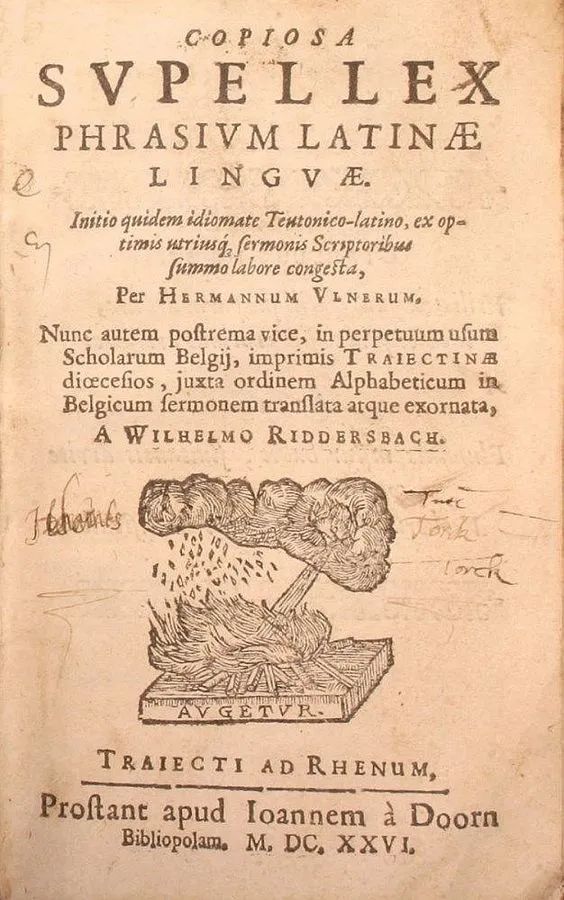
版式设计中文字的设计技巧分享
继版式三部曲之构图篇结束之后,时隔几个月终于迎来了这个系列的第二篇内容,就是“文字篇”。对上一篇内容还有印象的同学,应该记得我在结尾处预留的一个预告,当时我说的编排细节就是“文字”,为什么是文字呢?因为我们在排版时除了处理图片之外,剩下的就是要编排文字。今天的这篇文章也将围绕着“文字”展开,相信大家看完后会对“文字”有一个全新的了解,也将明白文字对于版面的意义是巨大的,处理好它,基本上你的版面也就编排的差不多了。好了,下面我们开始今天的内容吧。
首先来看几张不同类型的海报,第一张文字占比较高,第二张图片占比较高,第三张文字与图片占比是五五开。
然而不管是属于哪种类型的,它们的核心目的都是在传达信息。因为对于一张海报来说,我们不光会看还会去阅读它们。
平面设计就是通过文字来“说话”的。
而在广告设计中,图片的占比会非常高,因为广告多以图片为主,通过图片我们能大致的猜测出设计师想要表达的东西是什么。
总结一下:广告设计多以图片为主,意在通过图片传达概念;而平面设计则多以文字或图片为主,意在通过文字传达信息。
那么作为信息传达的载体,字体就显得格外重要了。下面我会从字体的分类、字体的搭配、字体的气质与设置细节着手,慢慢带领大家去认识字体,首先我们来看看字体的分类都有哪些。
其中书法体又细分为:楷书、行书、草书与隶书等。
在列举的这些字体中,最常用就是:黑体、宋体和圆体,而在书法体中,最常用的是楷书与行书。为什么说这些字体常用呢?因为在许多优秀的设计作品中,这些字体的出现概率都非常高,尤其是黑体与宋体。
其中最常用的就是:衬线体与无衬线体。理由与中文一样,它们也是使用率很高的字体,其次还有一个原因就是在以中文为主的设计中,它们与中文字体搭配起来比较契合。
拿黑体来说,与之搭配的英文字体就是无衬线体,因为它们的笔画特征相似度很高。
宋体搭配的就是衬线体,因为宋体的笔画特征是有粗细变化且有装饰线,而英文的衬线体也刚好有与之相似的地方。
而圆体则是搭配拥有相似特征的无衬线体。
因为常用的书法体通常使用毛笔书写,所以在笔画特征上没有与之相匹配的英文字体,大多数时候我们会选择用衬线体来搭配,具体原因我会在后面的字体气质环节为大家讲解。
虽然也有别的搭配方式存在,但我给大家提供的这些都是最常用和最安全的。说完字体搭配问题后,下面我们来看看这些字体,所包含的气质又有哪些。
首先是黑体,它具有科技感与现代感,这是由它简洁干练的笔画特征决定的。
其次黑体也能表现出运动与时尚的感觉,因为运动与时尚本就是偏现代的词汇。
接着是宋体,它具有文化与历史的气质,这个比较好理解。
而除了能表现出历史与文化感之外,宋体还能表现出清新与雅致的感觉,这是由宋体的笔画特征决定的,横细竖粗且末端带有装饰,与优雅精致的感觉十分契合。
圆体的特点也是非常明显的,在看到它时脑海中的第一印象就是可爱与卡通。
除了刻板印象外,圆体那种圆滚滚的笔画给我们的感觉还有安全和易亲近,所以圆体也能用来表现儿童与温暖感觉的题材。
一说到书法体,能直接联想到的关键词就是传统与历史,因为书法的演变就是我们汉字发展的轨迹。然后我们回过头来讲一下,为什么书法体可以和西文中的衬线体搭配。
原因就在于衬线体也具备书法体的某些气质,比如传统、文化、历史等。与书法体在早期的东方一样,衬线体在早期的西方也是主要的字体之一。
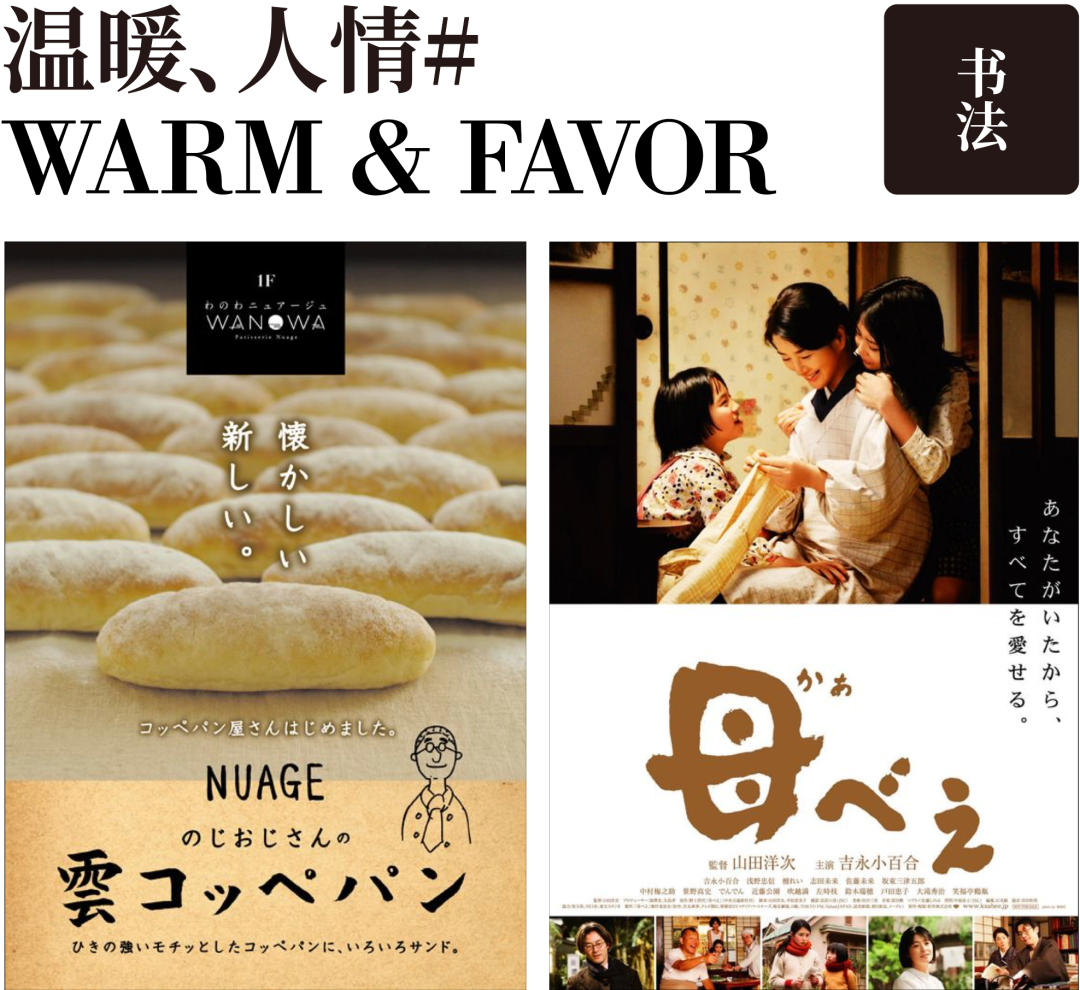
温暖、人情味儿,说到书法体可能很难联想到这两个词,但是书法体确实具备这种气质。跟黑体这种棱角分明的字体相比,书法体是手写出来的,它的笔画特征给我们的感觉就是有“温度”的。
在字符面板中,除了选择字体与改变字号以外,这两个区域相信大家用的还是比较多的,它们分别是:行距设置与字距设置。
拿行距来说,在使用时有几个比较常用的设置方法,比如用当前文字的字号乘以1.2、1.732或是2。不过,通过这个方法所算出来的数值只是一个参考,也就是说你可以在这个基础上做些调整。
比如:在计算出的数值的基础上进行递增或是递减,这时你要做的就是用眼睛去观察,觉得大了就减少一些,觉得小了就增大一些。
其中,用字号乘以1.2适用于标题。
比如上方那个标题的字号是40pt,那么行距的数值就是用40乘以1.2等于48。下方这个是在此基础上做的一个调整,稍微增大了一些行距。
字号乘以1.2适用于标题,而用字号乘以1.732或2则更适用于小字号的文字,比如内文。
上方是用字号乘以1.732的例子,字号是9pt,用它乘以1.732得出来的数值是15.588,四舍五入取个整数得到的行距就是16,下方这个是用字号乘以2得到的效果。
大多数情况下我建议大家用字号乘以1.732的行距,大小比较适中。
跟行距不同的是,基本上来说字距是无需调整的。当然还是那句话,要靠自己的眼睛来衡量,如果你觉得字与字之间离的很近的话,那么可以增大一些字距,反之,则可以减小一些。
其次就是,当你遇到一些偏轻松慢节奏的设计,比如典雅清新类的文学小说时,就可以适当的增加一些字距来营造这个感觉。
比如这两张海报,左边的是经典的居中结构,右边的是包围结构,构图都是可以的没有任何问题,但为什么看起来还是怪怪的呢?因为文字组没有刻画好。
为了让大家能更深刻地体会到文字组对于版面的意义,修改了这两张海报,其中构图不变只改文字组。
这个修改前后的对比还是非常直观的,可见文字组对版面的影响有多大。如果说构图是版面的骨架的话,那么文字组就是版面的五官,骨架再好五官不行结果也是可想而之的。
文字组分为:左对齐、居中对齐、顶对齐以及两端对齐。
其中与左对齐与顶对齐对应的有:右对齐与底对齐。
给大家找了一些各种对齐方式的案例。这是左对齐的形式。
这是右对齐的形式,与左对齐相比右对齐属于不常用的对齐方式,主要是出于易读性的考虑,但并不是说不能用。
这是居中对齐的形式,最经典的对齐方式之一。
这是顶对齐的形式,是文字竖排时最常用的对齐方式。
这是底对齐的形式,跟顶对齐相比也是属于不常用的对齐方式。
最后是两端对齐的形式,横排与竖排都可以使用这种对齐方式。
如果作品看得足够多,应该见过这种形式的组合,它同时包含了多种不同对齐方式,我们称其为“对齐组合”。
比如我们可以借鉴结构,以这个文字组为例,它的结构是这样的:两端对齐、中间的文字字号大,上下的文字字号小,按照这个套路我们来试着做一个组合。
在编排前,我们先阅读一下文案,通过文字可以得知,这是一个与篮球明星有关的内容,气质上来说会偏现代一些。
所以字体可以选择一款黑体,英文部分则搭配一款无衬线体。
根据之前总结到的这些特征,下面就可以开始编排文字了。
按照那个组合的套路,我们先将两端对齐中较大字号的文字给编排出来,而标题信息无疑是非常适合用来放大的。
接着再将上方和下方的小字号文字给编排出来。
其中要注意的就是这段文字的行距,我参考了logo的高度来进行设置。而整个组合中,字距是基本没有进行调整的。
值得一提的是,在两端对齐的文字组中,这种小大小的形式非常好用。因为它的节奏变化丰富,所以大家在做两端对齐的文字组时不妨试试。
这就是借鉴结构的效果了,精髓在于要多去分析别人的形式与套路,并从中获取做组合的灵感。除了能借鉴结构之外,我们还可以借鉴标题字数+结构,是什么意思呢?
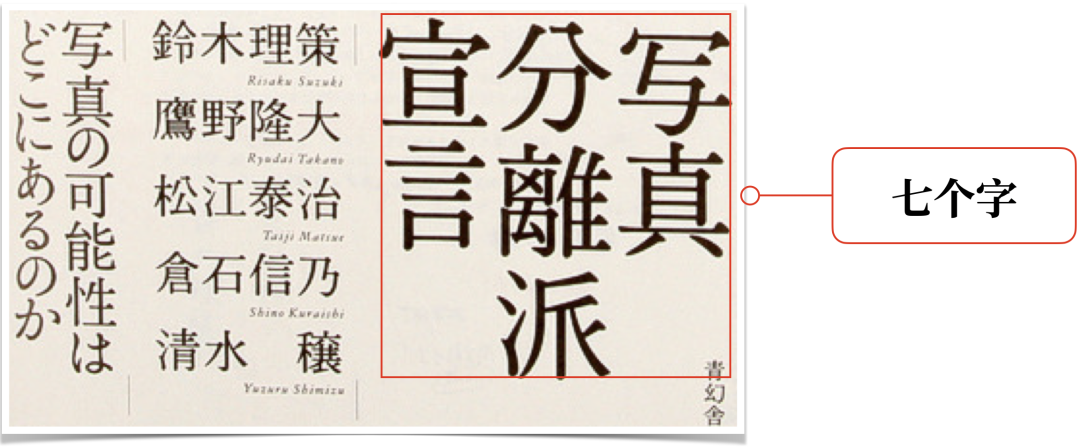
以这个组合为例,它的标题有7个字,整个组合是由顶对齐与两端对齐构成的一个对齐组合。
它的组合结构为小中大,按照这些特点我们来尝试借鉴。
这是要用到的文案信息,通过阅读文案可以得知,这是一个关于炸鸡套餐的内容。
通过去看kfc的各种物料,发现运用黑体的场景还是比较多的。
所以,在字体搭配上选择用黑体与无衬线体。
根据之前总结到的这些特征,下面就可以开始编排文字了。
按照小中大的特点,依次将信息给编排出来。
完成后可以在组与组之间,添加一根小线段用于连接,以起到过度的作用,如果大家现在回过头去看原图的话,也能发现这一特征。
其中,标题的行距就是用标题的字号乘以1.2算出来的。
字距我也做了调整,因为默认0的字距看上去有些拥挤。
可以看出跟原图相比,在不破坏组合结构的情况下,针对文字信息的编排是做了些调整的,比如:原稿最左侧是两行顶对齐的小文字,在借鉴时将它换成了logo,因为我们是要借鉴它的结构,而不是为了跟原稿做的一模一样,具体还是要根据我们的内容来合理编排。
首先我们来看这张图,一个标准的两端对齐、组合结构与之前那个是一样的,中间的字号大,上下的字号小。
除去这些外还有一个小特征就是,在大字号中间还有一层小字号的文字。
接着我们再来看这张图,它的特点就是图片叠压在了文字的上方。至于它的结构我们可以不用考虑,因为结构已经找好借鉴了。
这是要用到的文案与图片。通过文字可以得知,这是一个关于介绍昆虫的图书,且配有一张插图。这个插图的风格是手绘形的,偏写实一些没有那么的卡通。
结合这些特点我选择的字体搭配方式是,宋体配衬线体。
因为字体搭配这部分我又借鉴了一些相关风格的书,发现它们的字体搭配方式用宋体比较多。
分析完文案找到字体搭配方式后,在结合之前总结的一些组合特征,我们就可以开始编排了。
先将中间比较大的那层文字给编排出来,然后在它中间处置入一个小字号的文字。
中间层编排完成后再来编排上下层的文字,字号不用太大,整体注意好两端对齐。
调整字距的地方有两处,首先是标题,调整的原因在于默认值我觉得有些小了,其次是标题中间的那行文字,调整它的原因在于不想字号放太大。
因为是两端对齐的结构,不调整字距的话。标题中间那行文字只能通过放大字号来达到目,然而这个效果并不是我想要的。
综合考虑,选择了这个,最后,把图片置入进去叠压在文字的上方。
图叠压在文字上有一个无法避免的问题就是,被压住的文字会出现无法识别的情况,英文还好但是中文却不行,因为在这个组合中,中文是用来阅读的文字,英文仅充当装饰用。
既然中文是重要的信息,那为什么还要去遮挡它呢?因为有提示,通过这两个字你也能猜出来被压住的文字是什么。
这就是借鉴结构+表现手法的例子,多一张图片的加入,混合借鉴后的效果与原稿的相似度就会降低。
下面我们来看这张图,它既有顶对齐又有两端对齐的感觉,像这种组合我将它称为顶部两端对齐。
它的组合结构也是一个小大小的形式。
分析完上一个组合后,再来看看这个组合,值得借鉴的地方有两处,首先就是整体的结构,其次就是字体搭配。由于已经借鉴了上一个组合的结构,所以这个组合要借鉴的就是字体搭配。
在原图的这个字体搭配中,英文是最好判断的,这个字体是衬线体,中文则比较陌生了,既不像黑体也不像宋体。
感觉是被设计过的,不像是字库里的字体,我通过观察发现,它既有宋体横细竖粗的笔画感觉,又有黑体干净利落的特征。
所以,我在字库字体中找到了一款具有类似感觉的字体:姚体。
在字体搭配上选择用姚体搭配衬线体。这里需要强调的一点是,在挑选字体借鉴的过程中已经考虑到了与文案的气质相匹配的问题,下面我们就来看看文案。
标题叫“遇见你之前”,给人的感觉比较文艺,而姚体我们前面也分析过了,它是具有宋体特征的,而且笔画细长,整体给人的感觉就是比较文艺的。
接下来做烘托氛围的工作,先把底色换成夜空的黑色,然后配上图片。
接着更换字体的色彩恢复识别性,其中黄色的部分是为了与白色部分做区分。
然后给腰封换上色彩以恢复下方的文字的识别性,再挑选一些信息,在它们的下方配上黄色,目的是为了与上方的色彩做呼应。
最后,将书脊编排出来,这个案例就编排完成了。
以上就是版式三部曲之文字篇的所有内容了,回顾一下,由两个部分组成。第一部分是:字体的分类、字体的搭配、字体的气质与设置细节。具体包括:字体有哪些不同的类型、在选中字体的类型后,要如何选择与之搭配的英文字体。字体气质主要讲的是,不同类型的字体都有哪些味道,它的意义在于当你确定好项目的风格后,可以根据不同字体的气质,快速的找到与项目定位契合的字体。
第二部分主要讲的是:文字组的刻画与借鉴,其实对于新手而言,刻画文字组的过程就是借鉴的过程,因为我们都需要在借鉴的过程中逐步积累编排的经验,所以学会如何借鉴对于我们的成长是至关重要的。这一期要说的就是这些,我们下期再见,拜拜。